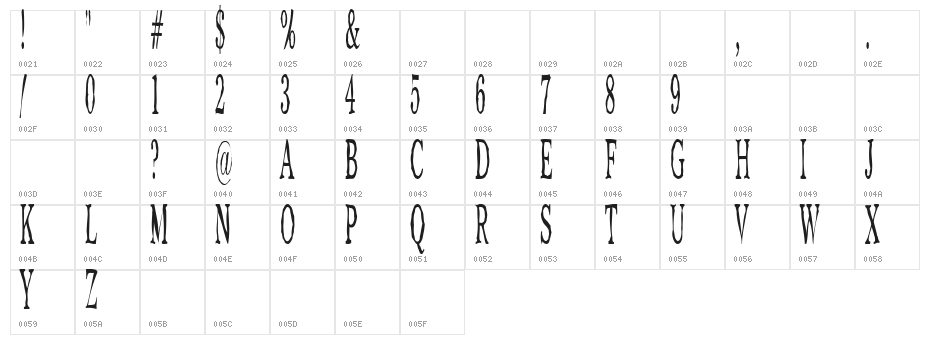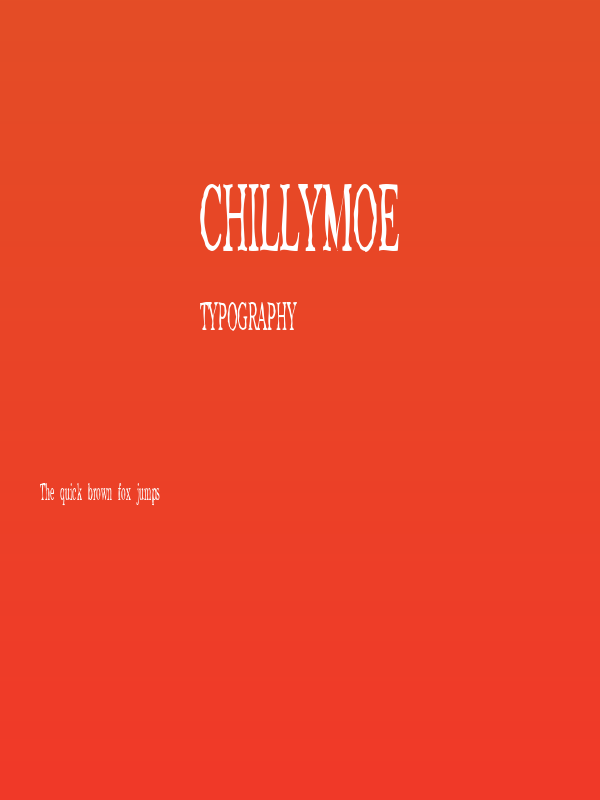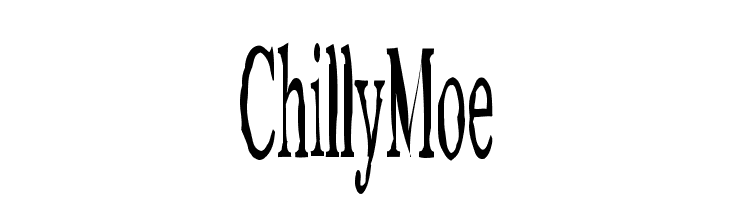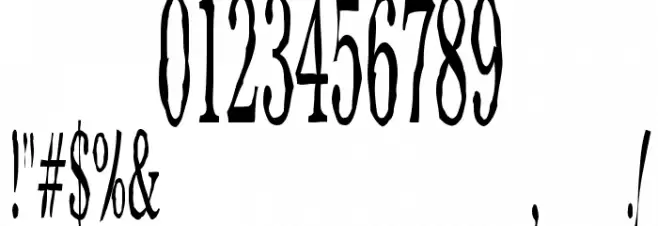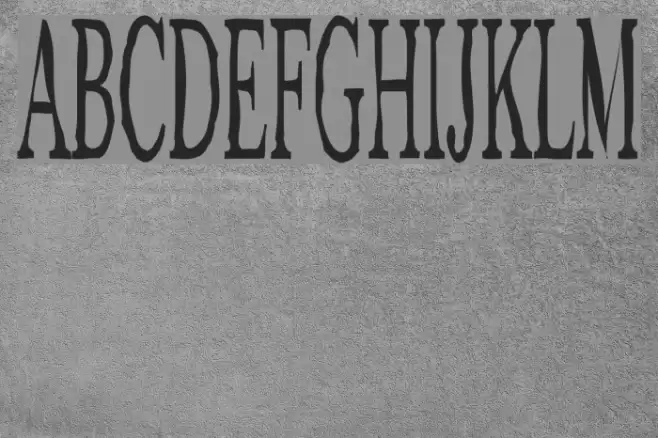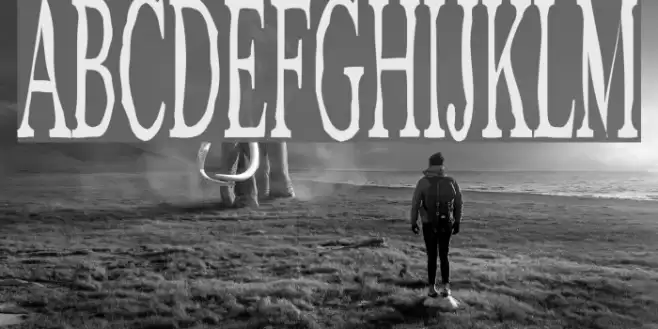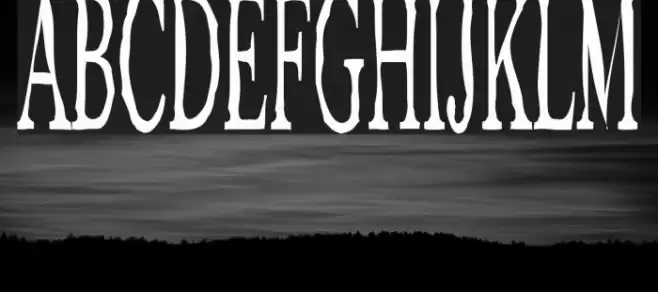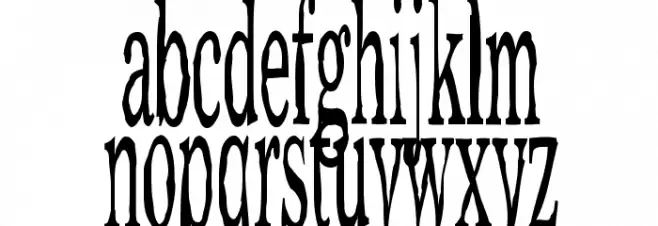
ChillyMoe Font
| Caso de uso | Logos, Posters, Artistic Branding |
| Projetos propostos | Ideal for creative projects such as posters, album covers, or branding for artistic ventures. It can also be used in digital art or as a decorative element in graphic design. |